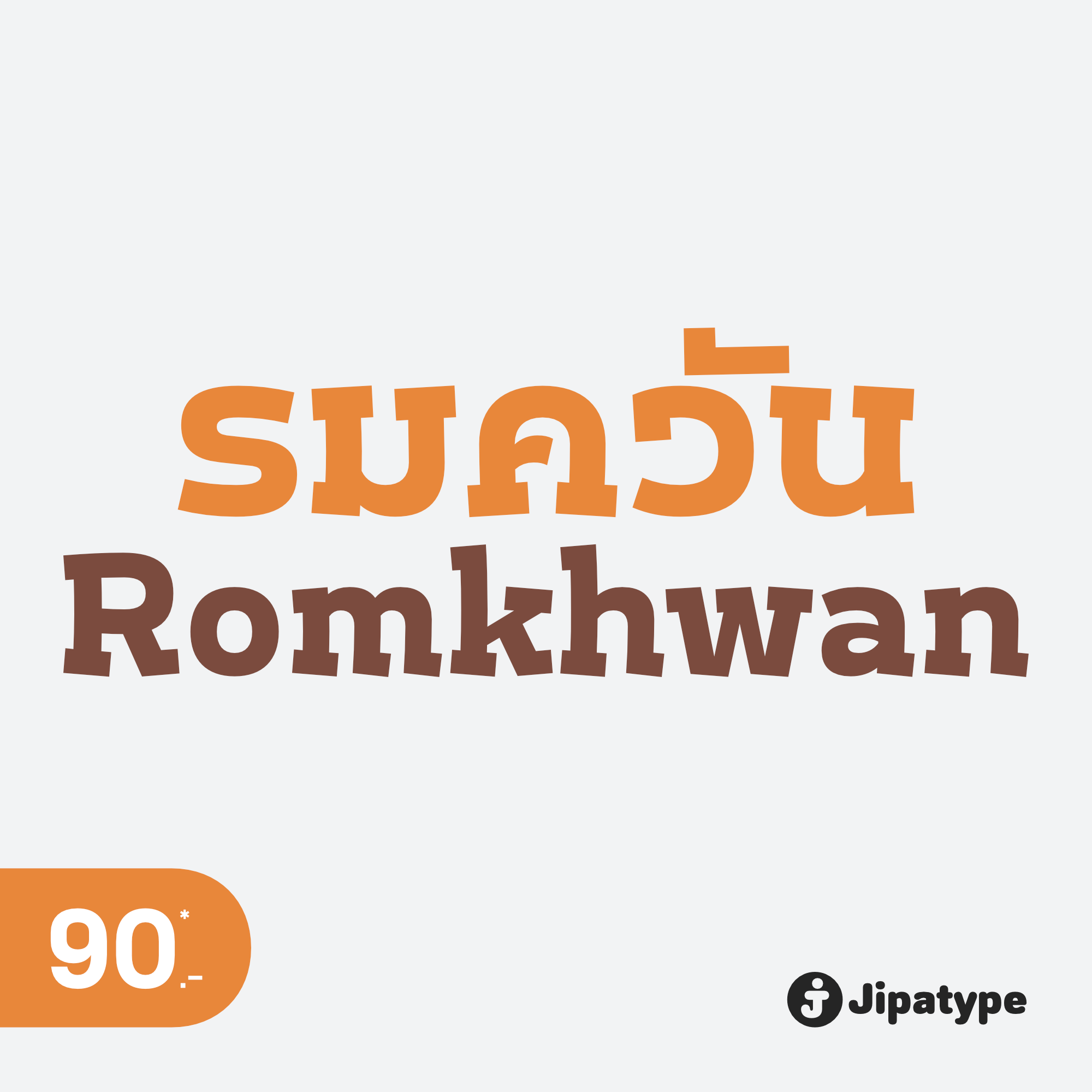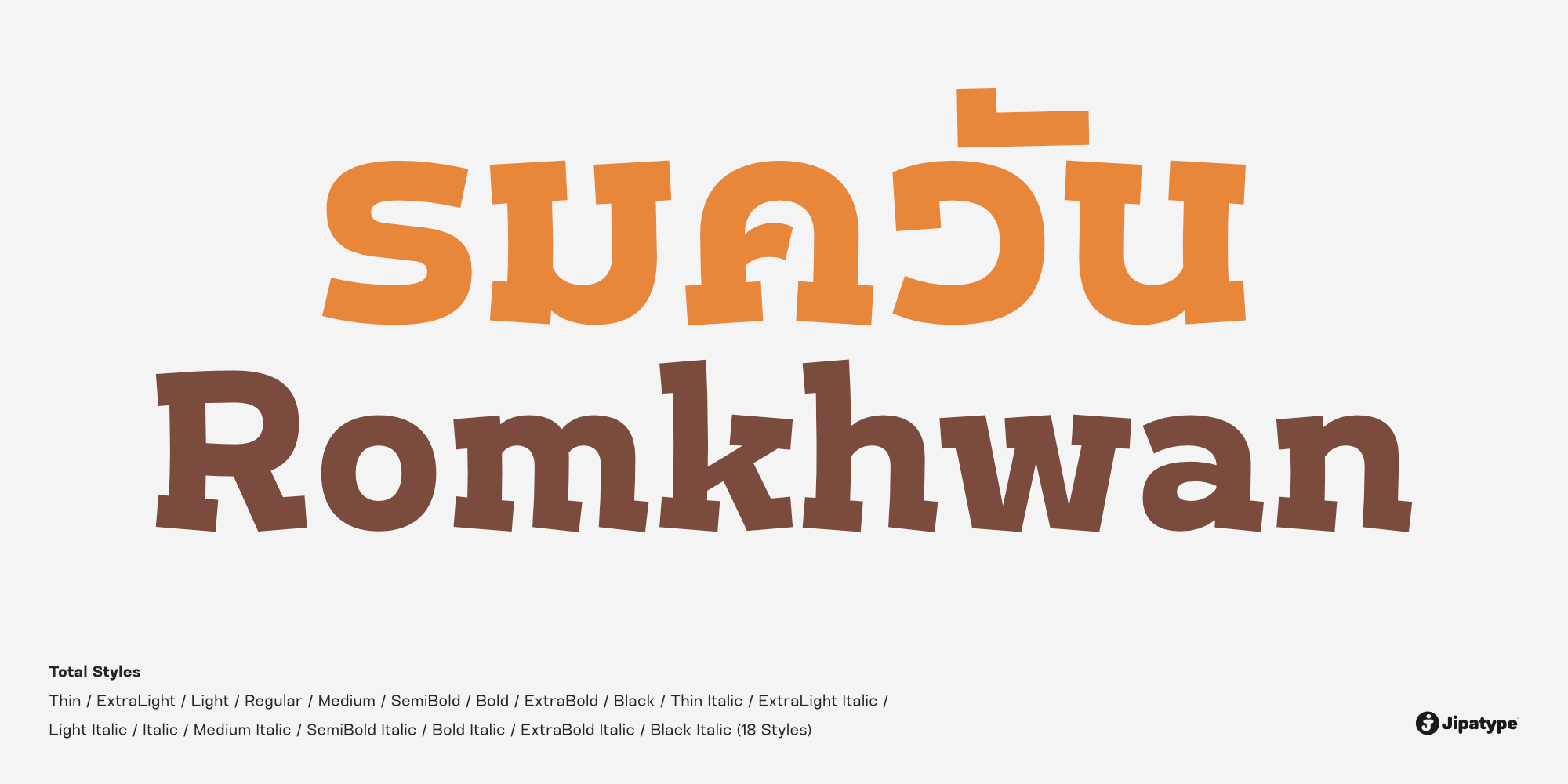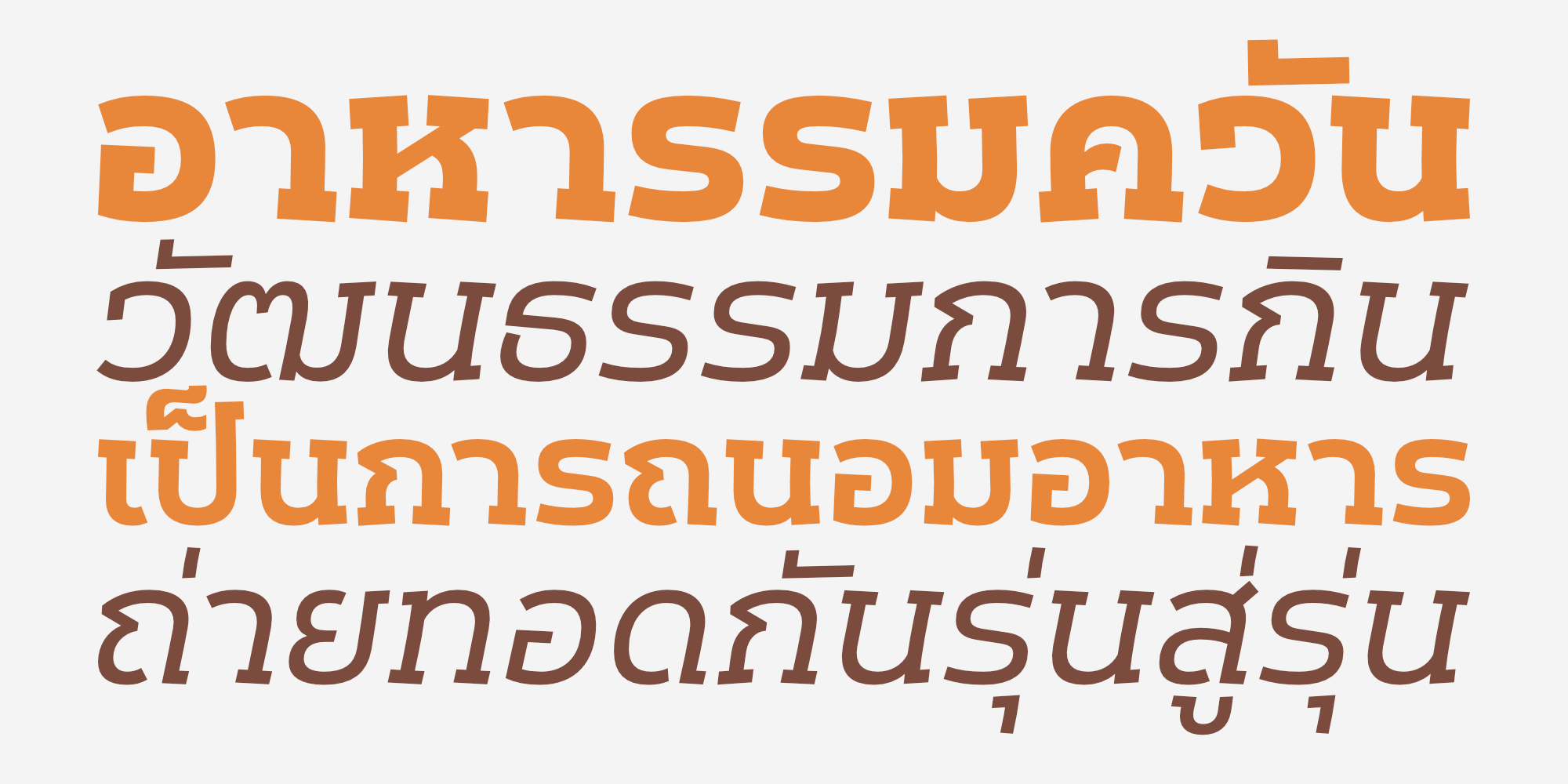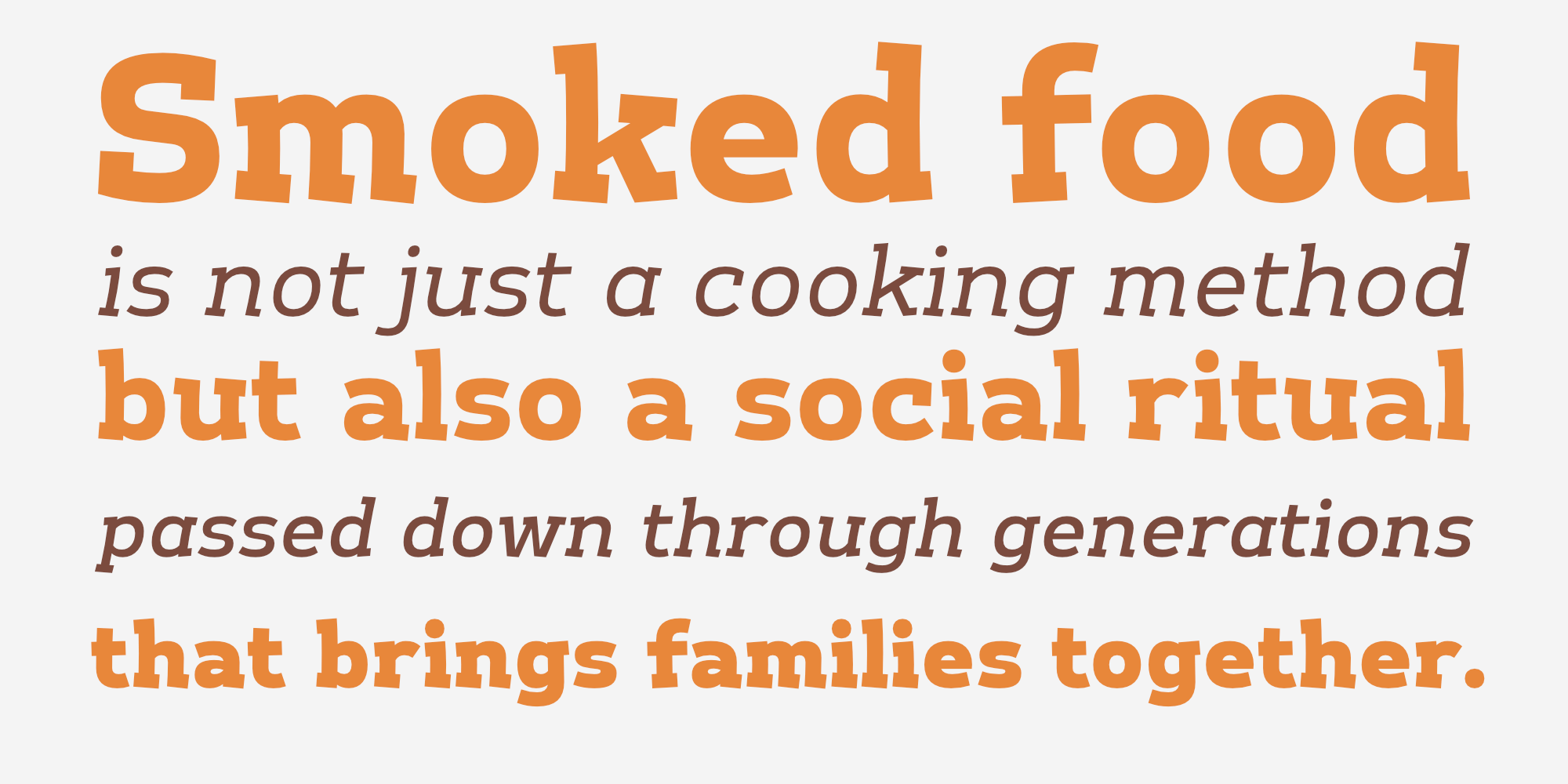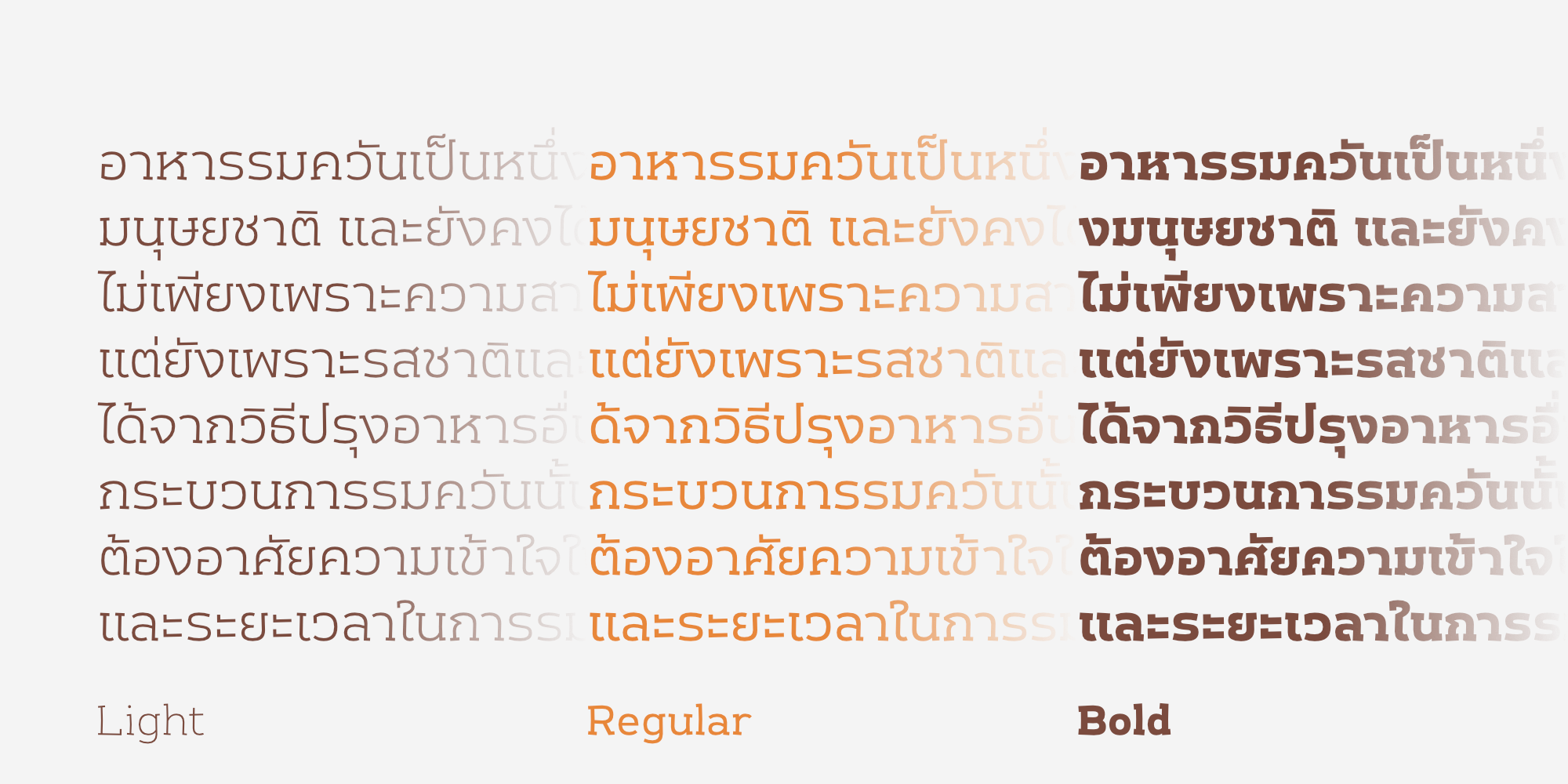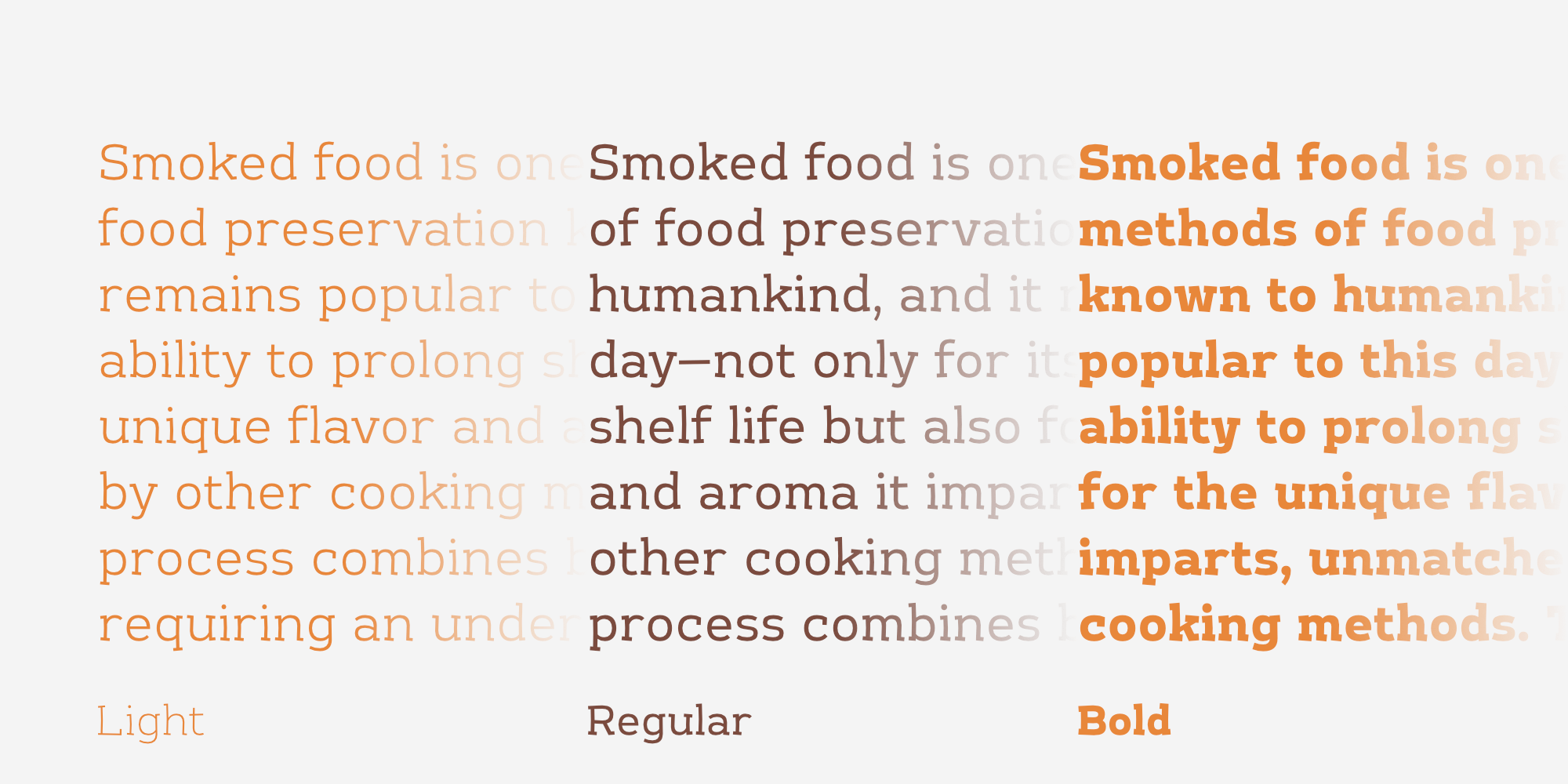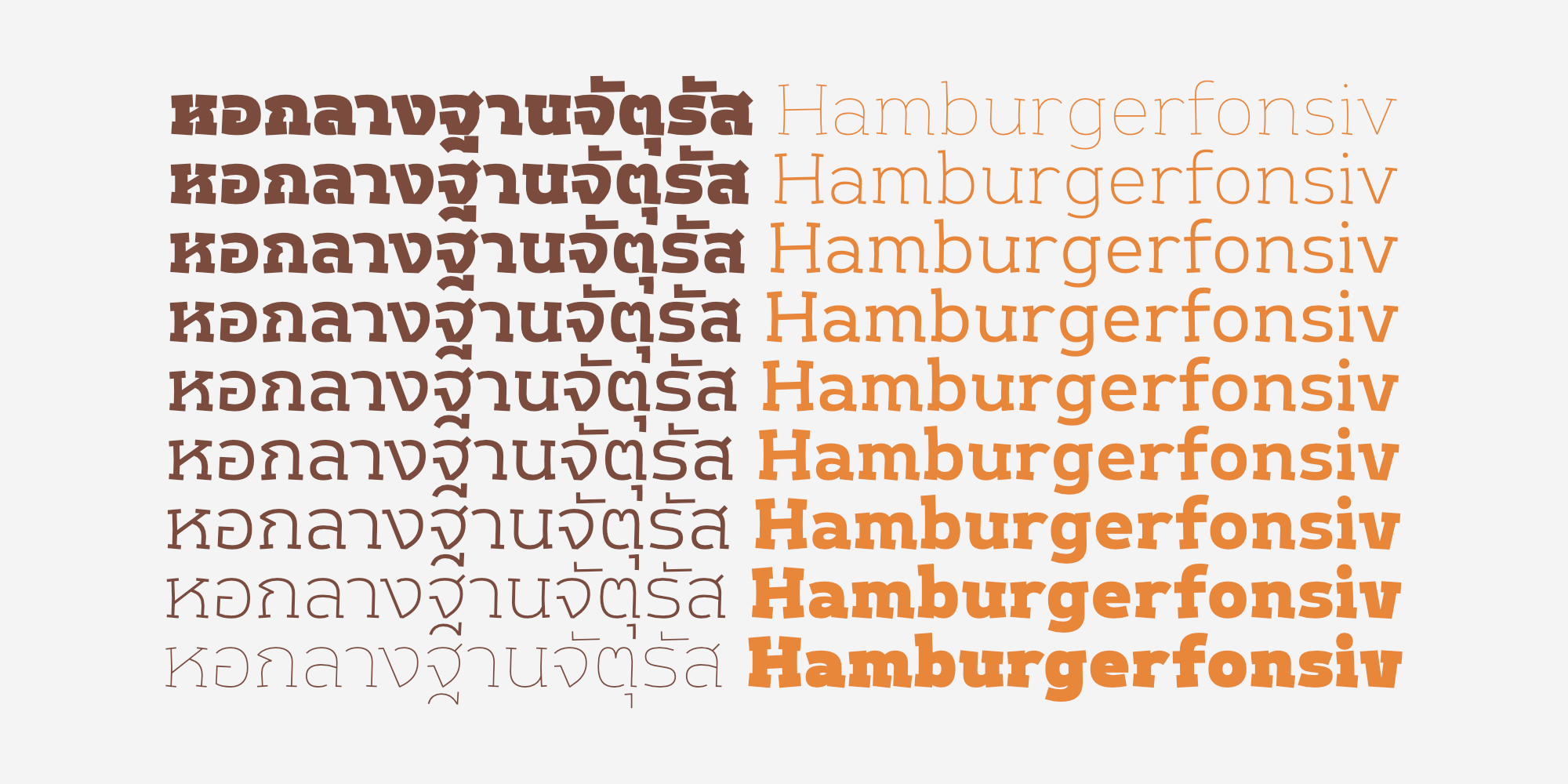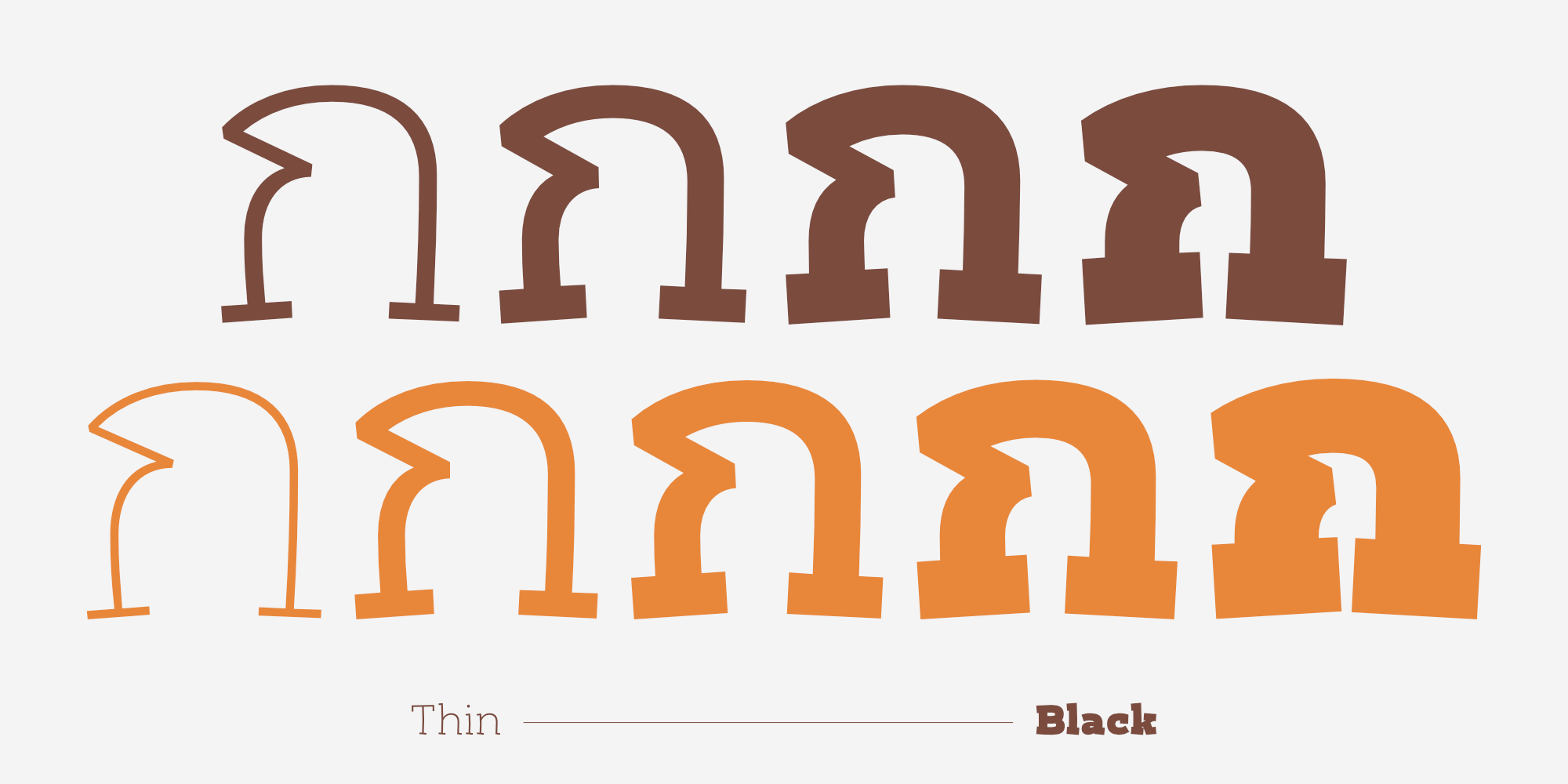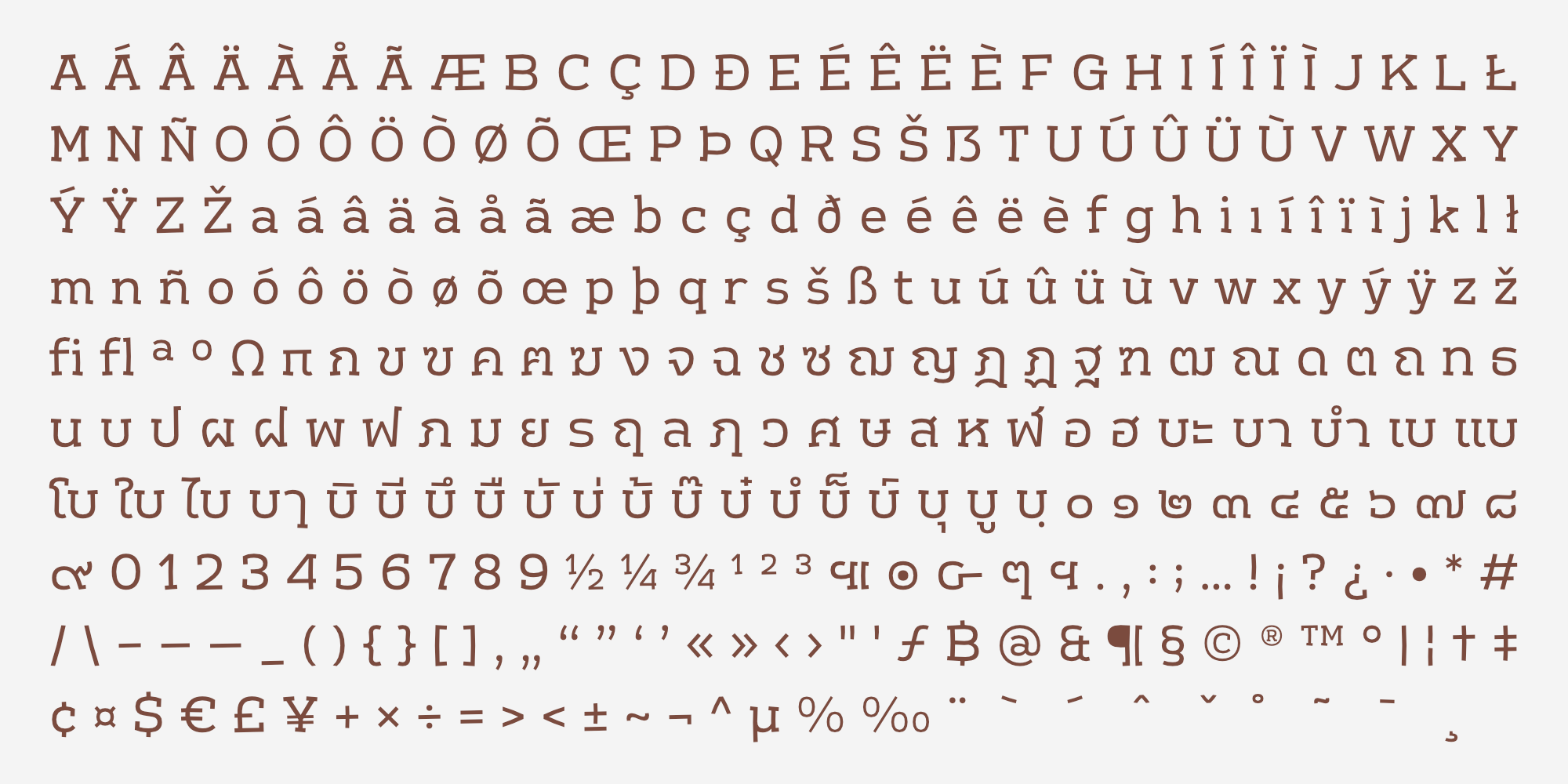
รมควัน เป็นฟอนต์แนวสลับเซอริฟ ที่มีความสนุกแบบไม่หลุดกรอบ เล่นได้แต่ไม่หลุดโลก มีคาแรกเตอร์ที่ดูขี้เล่นแต่ยังคงสมดุล เหมาะกับงานที่อยากให้ดูสบาย ๆ แต่ยังมีโครงสร้าง
ตอนออกแบบฟอนต์นี้ ผมนึกถึงภาพไส้กรอกที่กำลังย่างอยู่บนตะแกรงร้อน ๆ ควันลอยฟุ้งอยู่เต็มไปหมด เลยเป็นที่มาของชื่อ “รมควัน”
ฟอนต์นี้มาพร้อมกับ 18 สไตล์ และรองรับทั้งภาษาไทยและ Latin-1 ครบถ้วน พร้อมใช้กับงานหลากหลายแนว